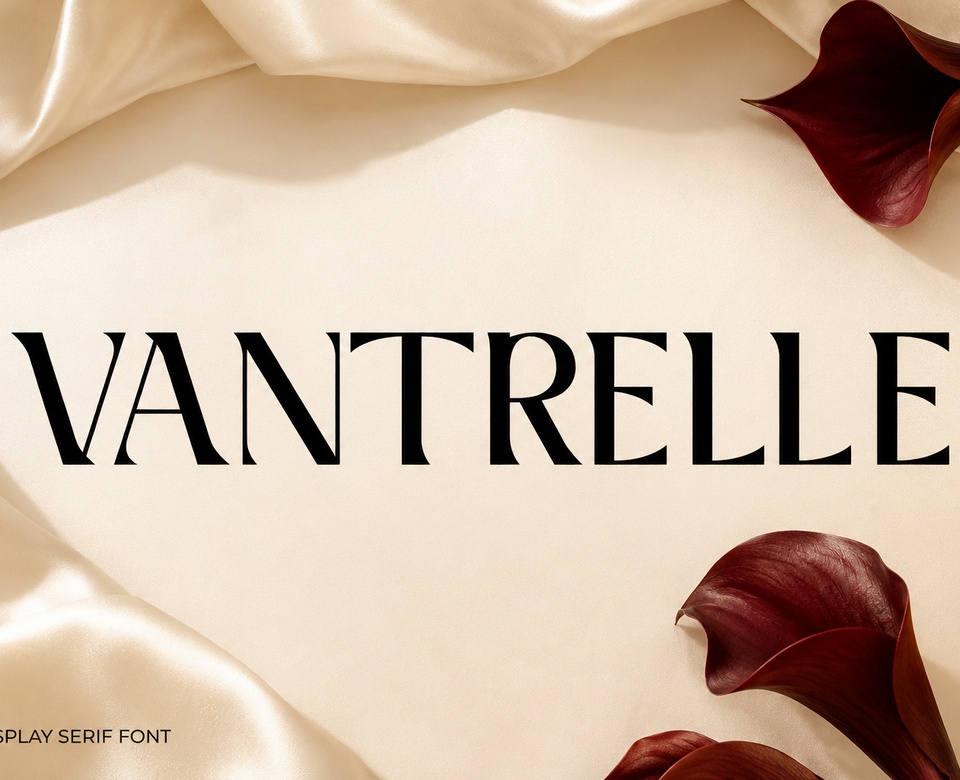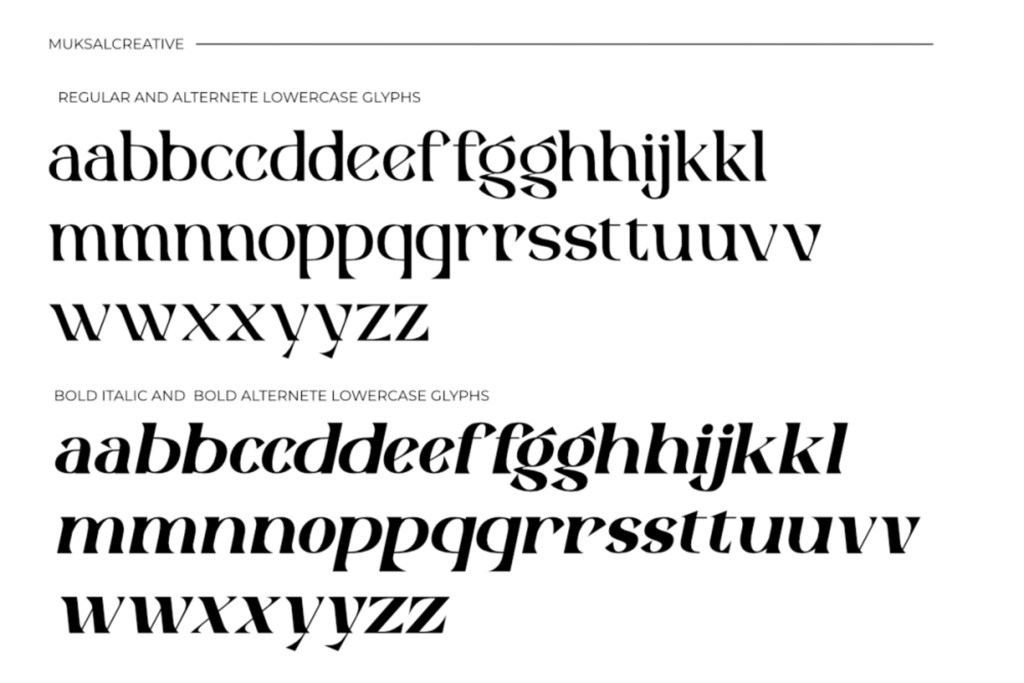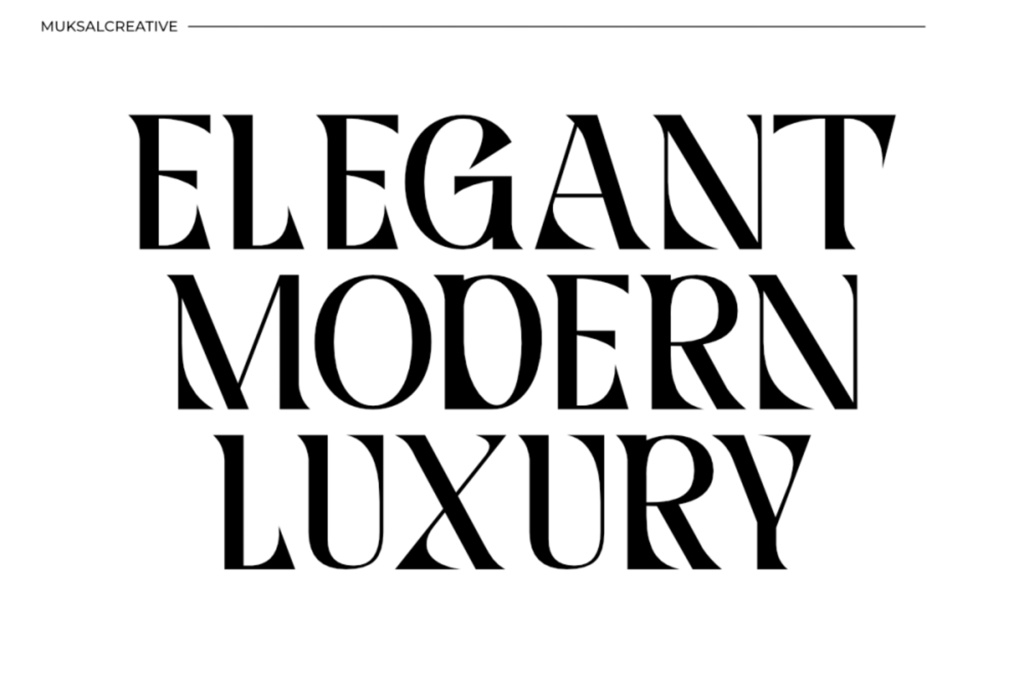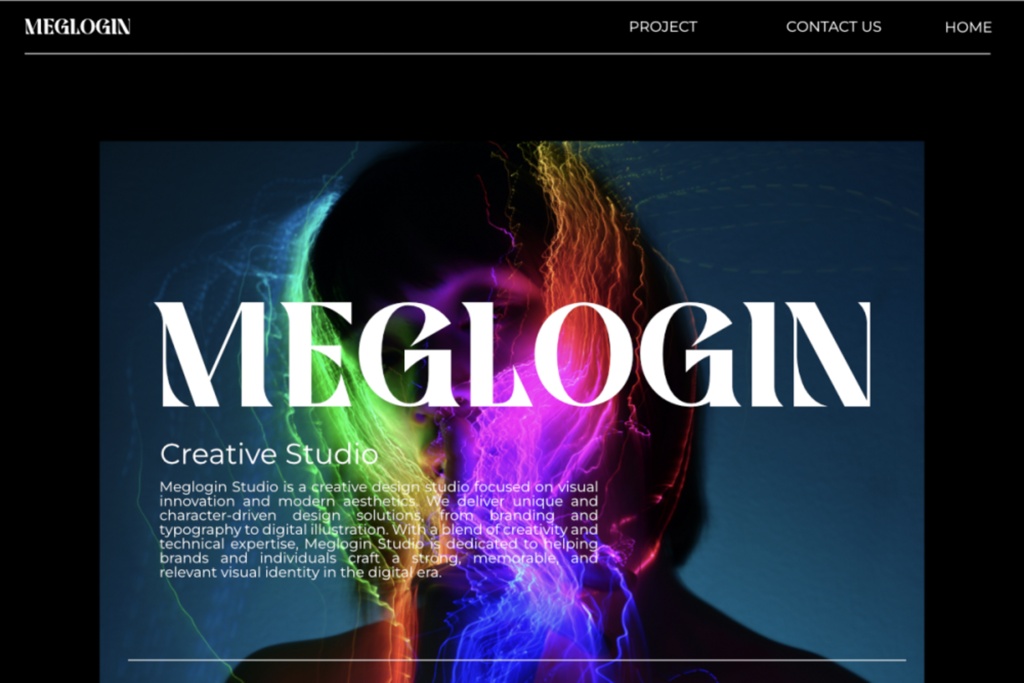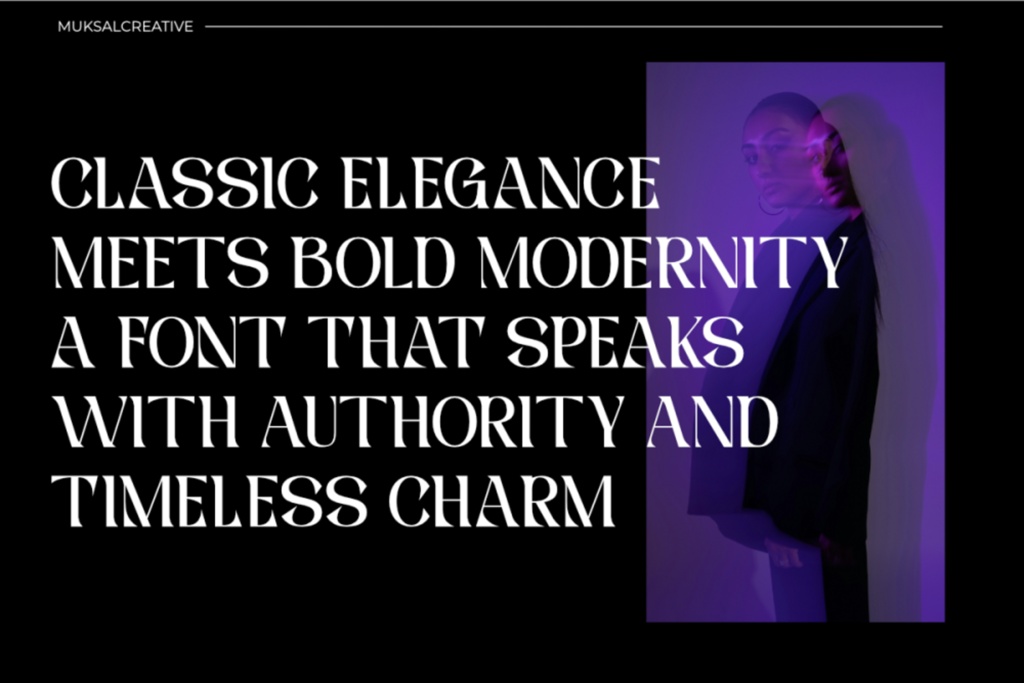
VANTRELLE - 高級ディスプレイセリフフォント
VANTRELLEは、クラシックなエレガンスとモダンなラグジュアリーの境界線を巧みに操る、大胆でドラマチックなディスプレイセリフフォントです。どこかミステリアスな雰囲気を漂わせ、自信に満ち、洗練され、見る者を惹きつけます。言葉を発する前から特別な存在感を放ちたいブランドのために作られた、ラグジュアリーなセリフフォントです。ありきたりな高級フォントはどれも同じように見えますが、VANTRELLEは違います。 このエレガントなセリフフォントは、RegularとItalicの2つのスタイルを収録したフォントデュオとして提供され、1回のダウンロードでラグジュアリーなブランディングに必要なツールキットがすべて揃います。自信に満ちたステートメント、見出し、ロゴマークには、直立したRegularを、編集記事の引用文や雑誌のレイアウトには、動きと強調を演出するItalicをご使用ください。各スタイルには、大文字、小文字、数字、句読点、アクセント付き文字を含む279のグリフが収録されており、多言語プロジェクトにも対応します。 主な特徴: RegularとItalicの2つのフルスタイル - ステートメントに最適な直立スタイルと、動きとドラマチックな印象を与える斜体スタイル。 スタイルごとに279グリフを収録。アクセント付き文字を含む完全な文字セットで、多言語に対応しています。 OpenType GSUB/GPOS、スタイル別文字(ss01)付き。洗練されたスペーシングと代替文字により、ロゴのレイアウトから見開きページまで、バランスの取れた書体を実現します。 スタイルごとに4つのフォーマット(合計8ファイル)に対応。OTF、TTF、WOFF、WOFF2に対応しているため、印刷物、Web、アプリデザインなど、あらゆる用途でそのまま使用できます。 クリーンなPaperMoonメタデータ。インストール可能な埋め込み(fsType=0)、Copyright (c) 2026 PaperMoon、商用利用可能。 このフォントが真価を発揮する用途:ラグジュアリーブランドやブランドアイデンティティ、エディトリアルデザインや雑誌の表紙、ファッションルックブック、化粧品や美容製品のパッケージデザイン、ブティックホテルのアイデンティティ、高級ウェディング招待状、ロゴデザイン、ポスター、大型ディスプレイにおけるヒーロータイポグラフィなど。美しさがすべてを左右するプロジェクトのために作られた、プレミアムセリフフォントです。 互換性:Adobe CC(Illustrator、InDesign、Photoshop)、Figma、Canva、Procreate、Affinity、およびOTF/TTFファイルを読み込めるあらゆるアプリケーションで動作します。WOFF/WOFF2ウェブフォントは、@font-face経由でWebプロジェクトやサイトビルダーに直接組み込むことができます。WindowsとMacへのインストールは簡単です。 ライセンス:この商品はCubebrush商用ライセンスに基づき商用利用が可能です。クライアントワークや販売商品にご利用いただけます。クレジット表記は不要です。グリフのアウトラインは手書きで作成された書体(AI生成の文字ではありません)なので、商用プロジェクトで安心してご利用いただけます。 あなたの次のラグジュアリーブランドアイデンティティに、静謐なドラマ性を与えましょう。VANTRELLEをカートに追加して、デザインを始めましょう。 今すぐ購入 $9.00 バンドルに追加して割引 20ドル以上の商品を追加すると、バンドルが5%オフになります。 X http://cbr.sh/863ewk このURL経由での売上には5%の手数料がかかります。ぜひシェアしてください! この製品を報告する